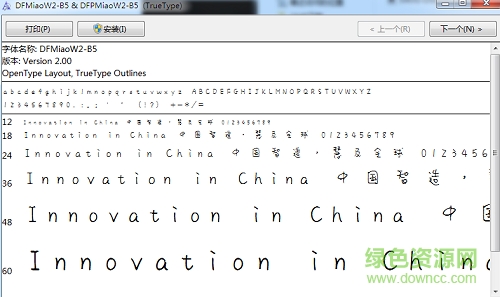
華康妙風(fēng)體是華康打造的一款非常有特色的電腦漢字簡體字體,字體筆畫工整,整體效果給人清新的感覺,喜歡的朋友歡迎到綠色資源網(wǎng)下載體驗(yàn)!
華康妙風(fēng)體,這字體是一款美術(shù)風(fēng)格的繁體字庫,以其清新自然的設(shè)計(jì)、繼承也創(chuàng)新的完美結(jié)合,受到大家的追捧,體整體上看上去偏卡通色彩,非常適合用于藝術(shù)創(chuàng)作!